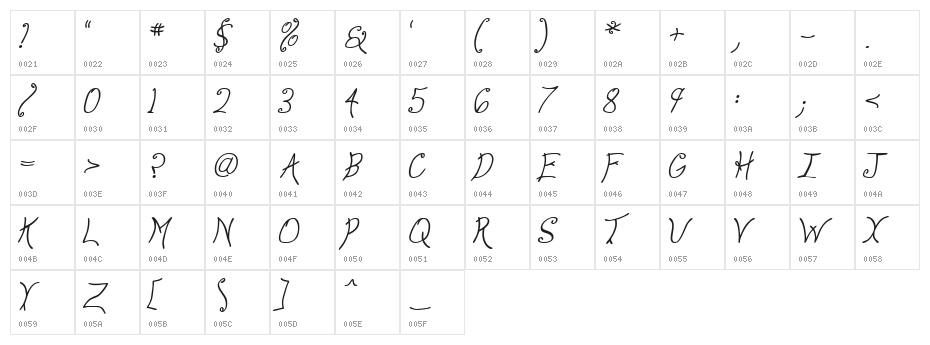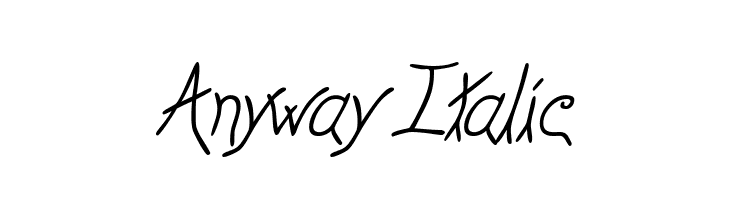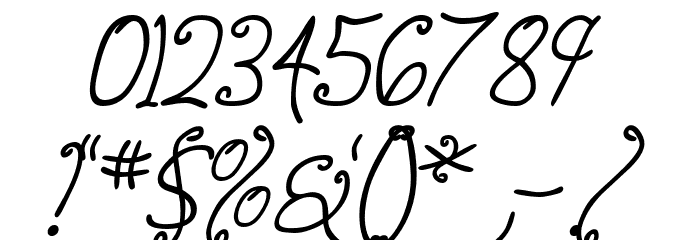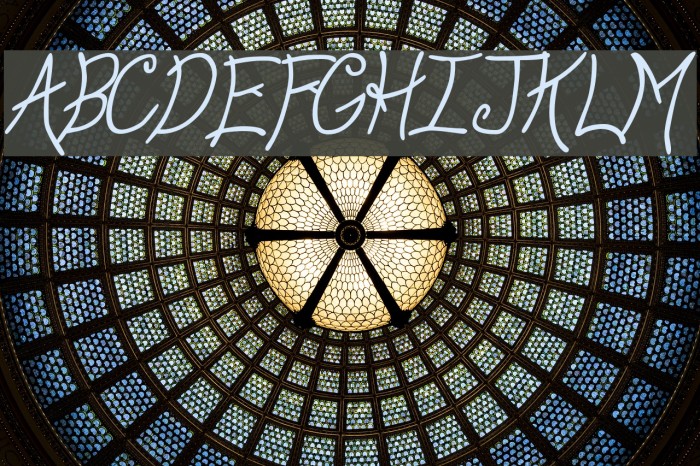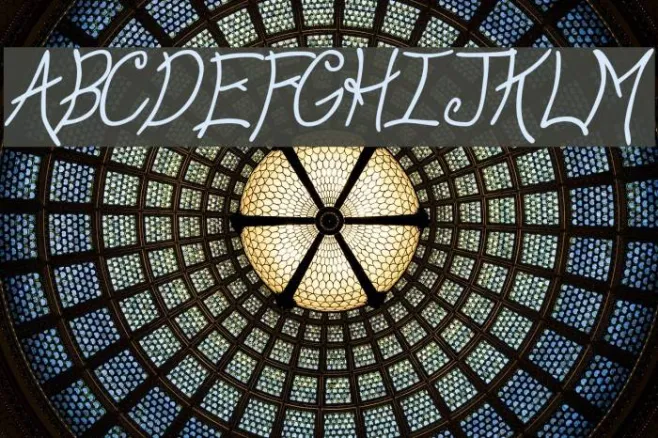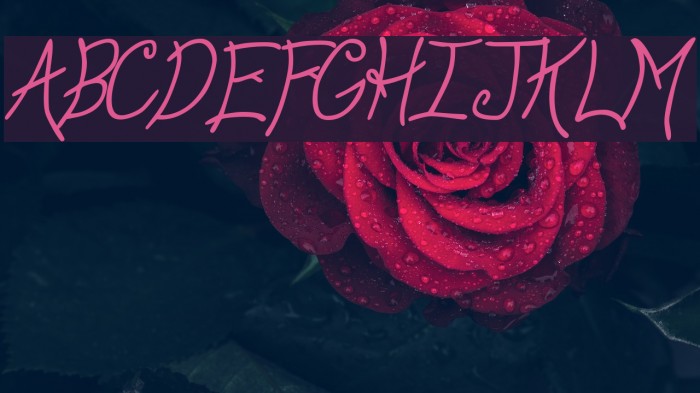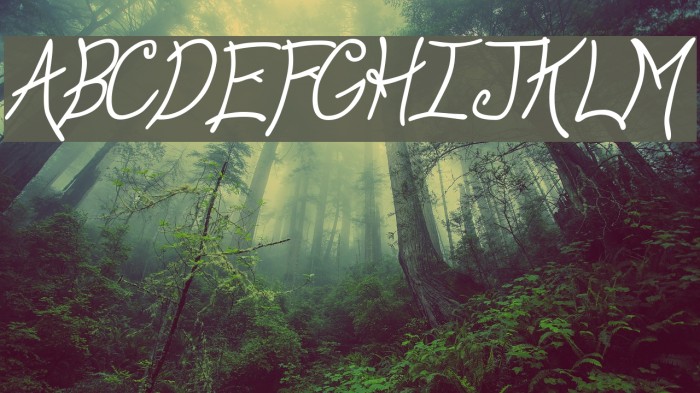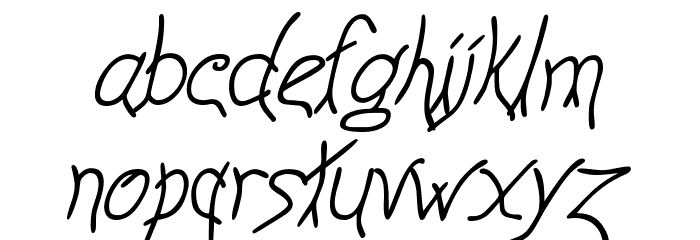
Anyway Italic Font
✎ Script
| Anwendungsfall | Headlines, Logos, Artistic projects |
| Vorgeschlagene Projekte | Ideal for greeting cards, invitations, artistic posters, and branding materials that require a personal touch. |